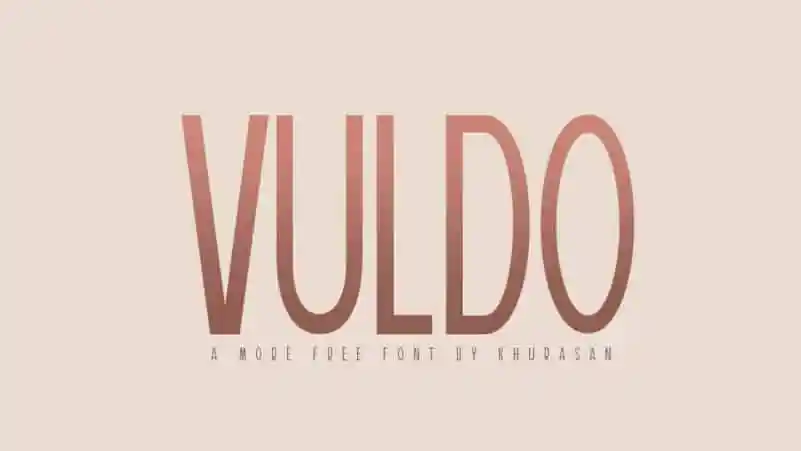
Vuldo Sans Serif Font – Download Grátis
Vuldo Sans Serif é uma nova fonte moderna com uma versatilidade criativa única. Ela destaca-se por sua atrativa agressividade e sua elegância, tornando-a um tipo moderno e condensado de sans serif perfeito para a mídia digital, identidades visuais, headlines e cartazes. Essa fonte é ideal para estilos futuristas ou contemporâneos dos sites de revista, marcas sociais e publicidade. Com seu design minimalista mas forte, Vuldo Sans Serif atende ao requisito de elegância moderna e facilmente incorporável em diversos ambientes visuais. Engane-se se acredita que esta é uma fonte comum ou simples: ela traz um toque único que certamente irá impactar sua identidade visual digital.